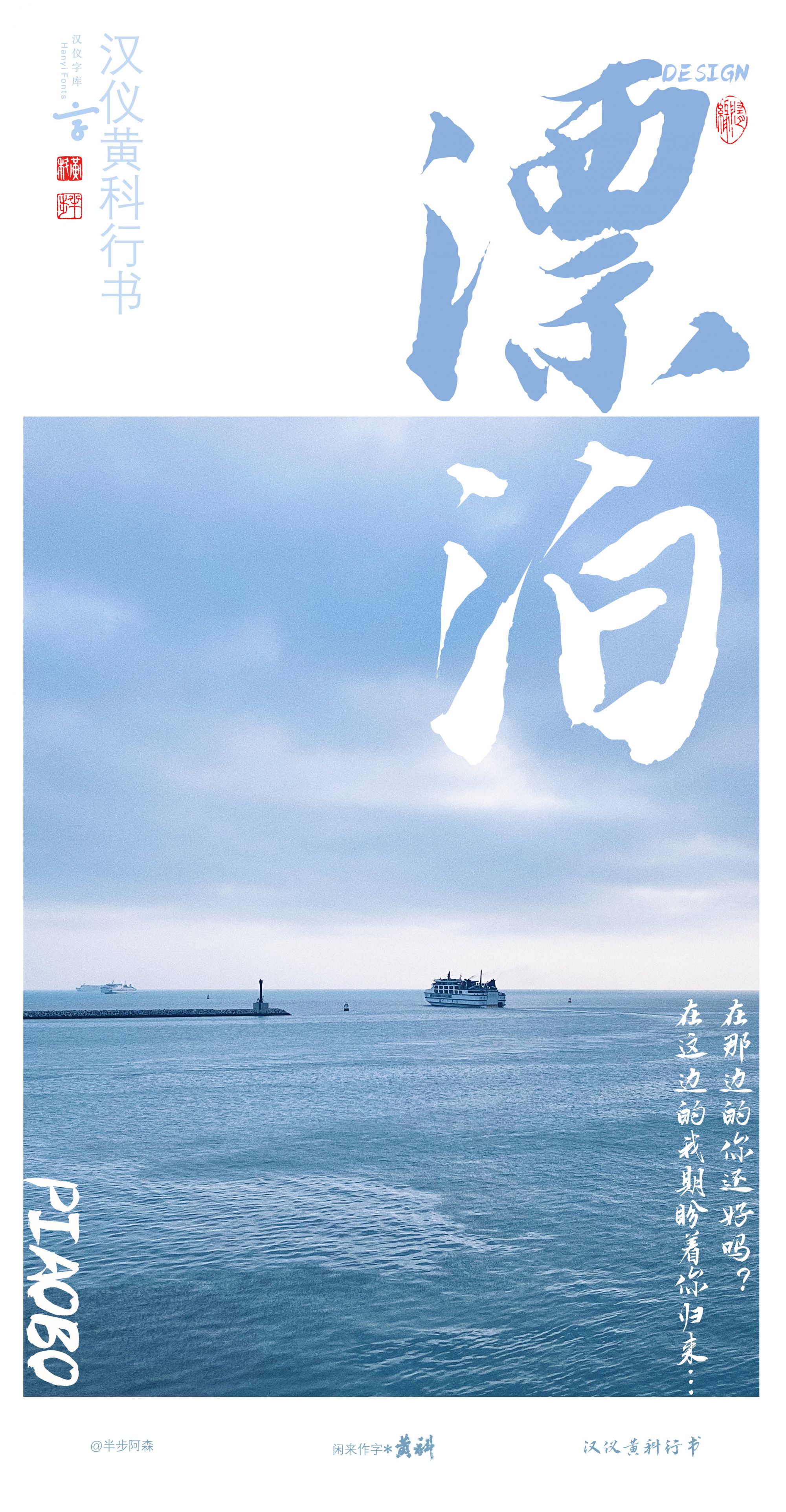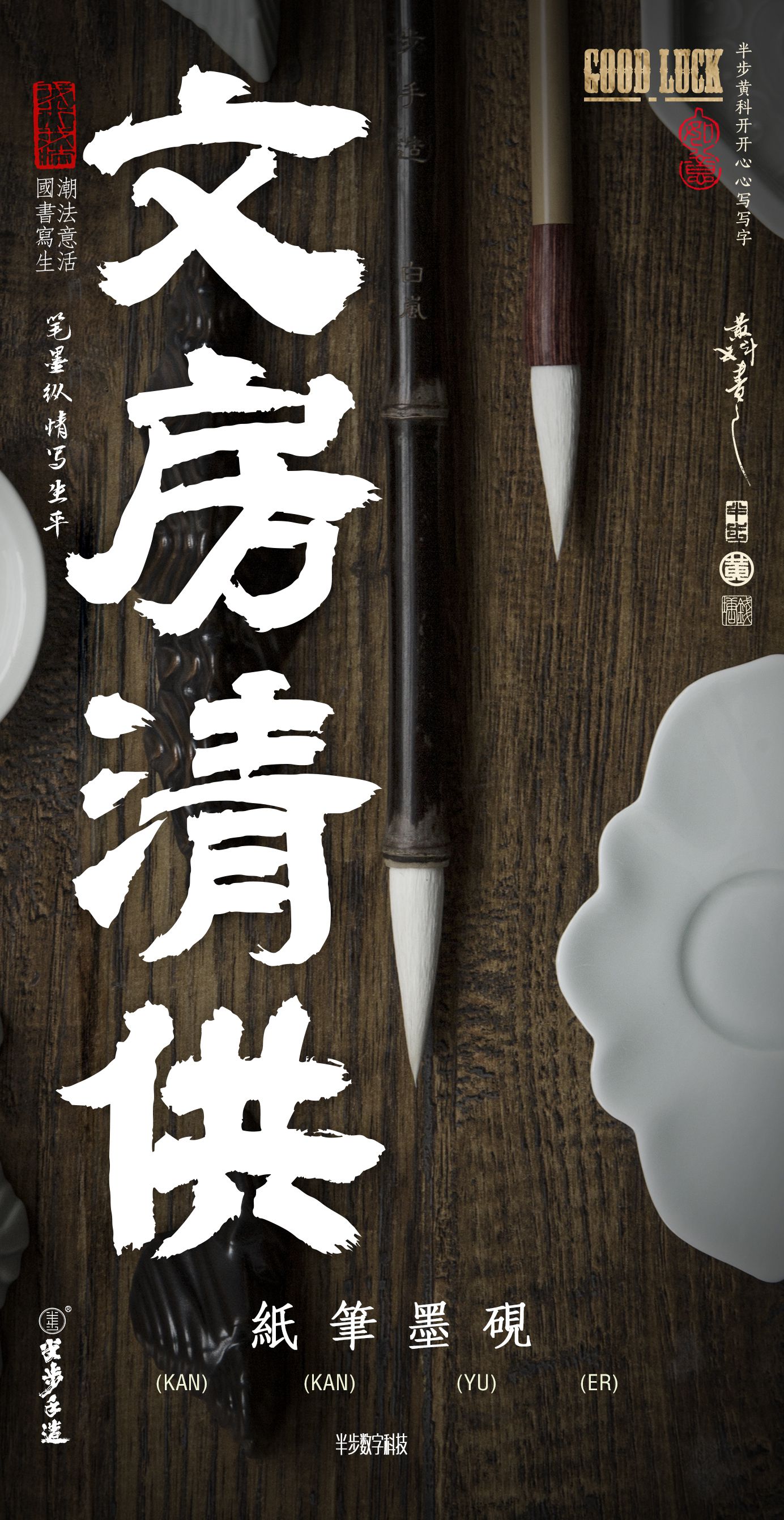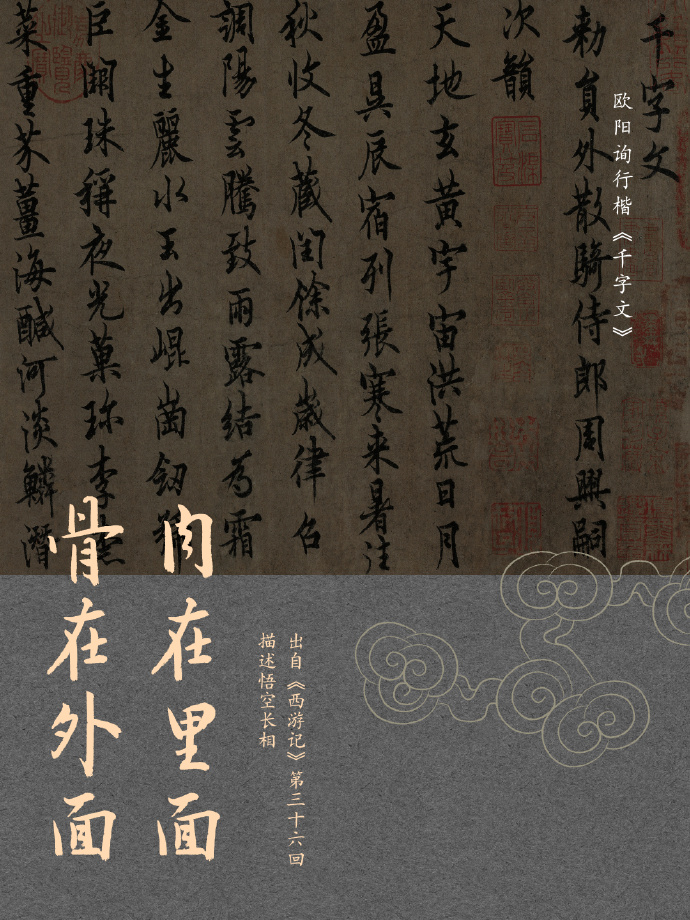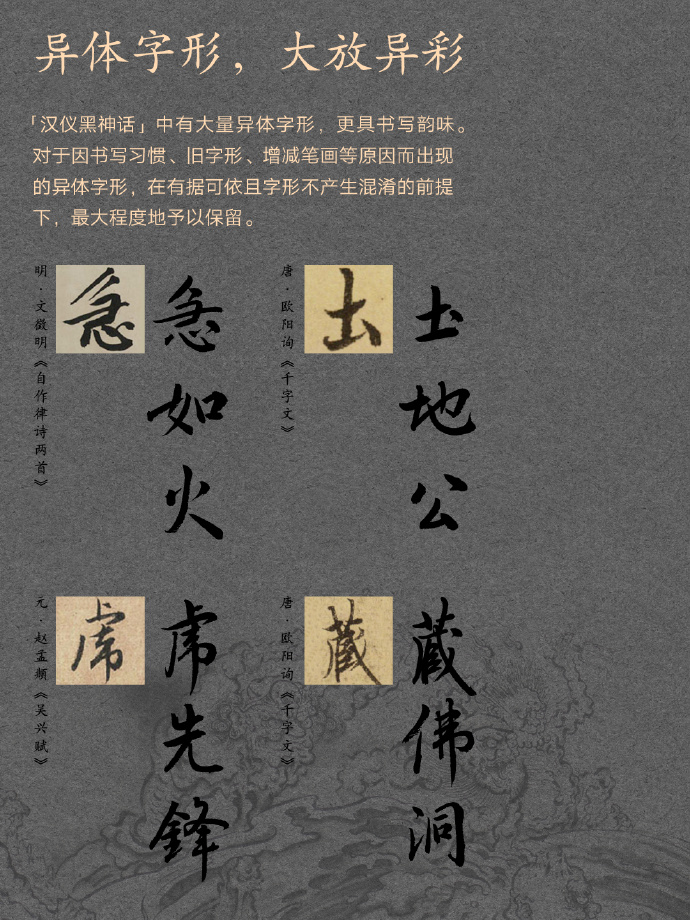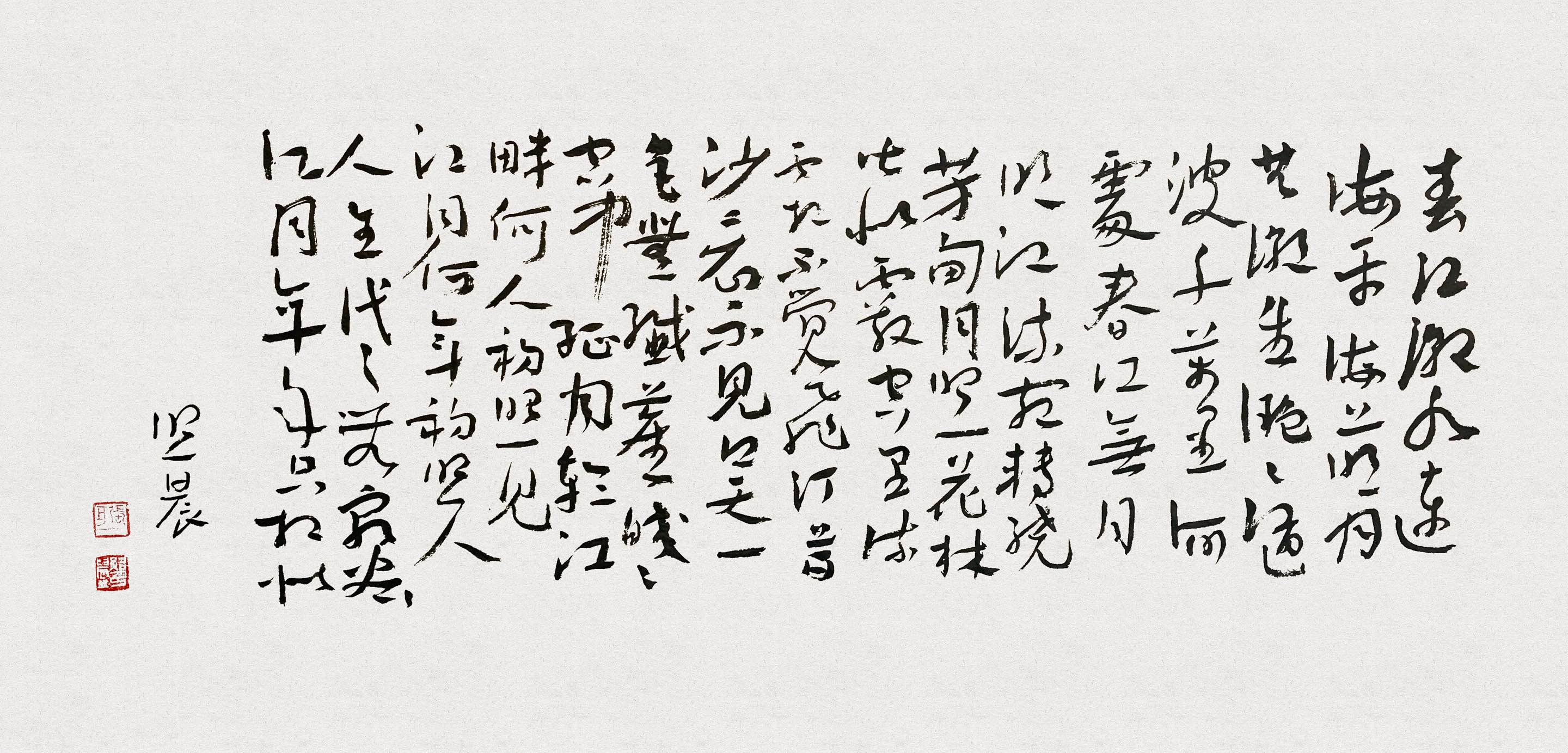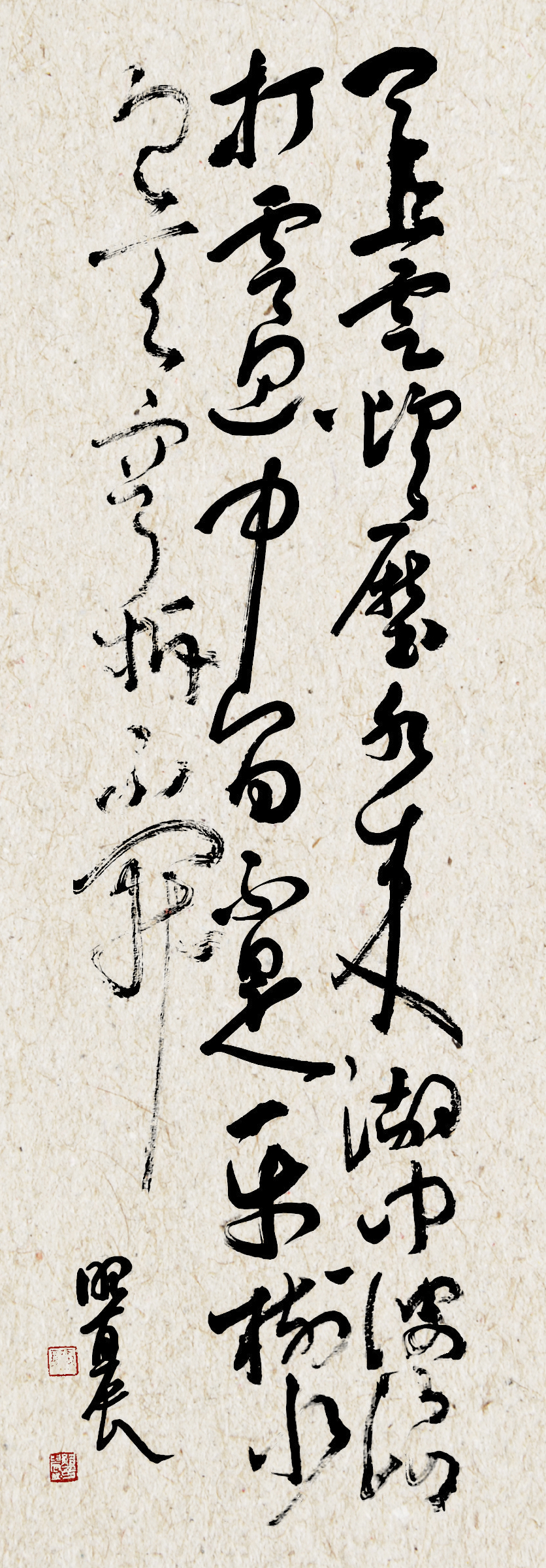
{{tag.name}}今年年中大火的《黑神话:悟空》以其独特的东方美学和视觉设计震撼了全球玩家,其中的字体更是将书法与游戏风格巧妙配合,呈现出力与美的融合。
工作坊特别邀请到《黑神话:悟空》游戏标题字体作者黄科老师、书法字体汉仪黑神话书写者张照晨老师为大家分享讲解黑神话悟空手写字的故事。
黄科
◈《黑神话:悟空》标题字体设计师
◈ 汉仪黄科榜书、汉仪黄科行书、汉仪黄科壮隶字体作者
黄科老师题写的游戏标题
黄科老师题写的影视剧标题
汉仪黄科榜书
汉仪黄科行书
汉仪黄科壮隶
汉仪黑神话
汉仪晨妹子
张照晨老师更多书法作品